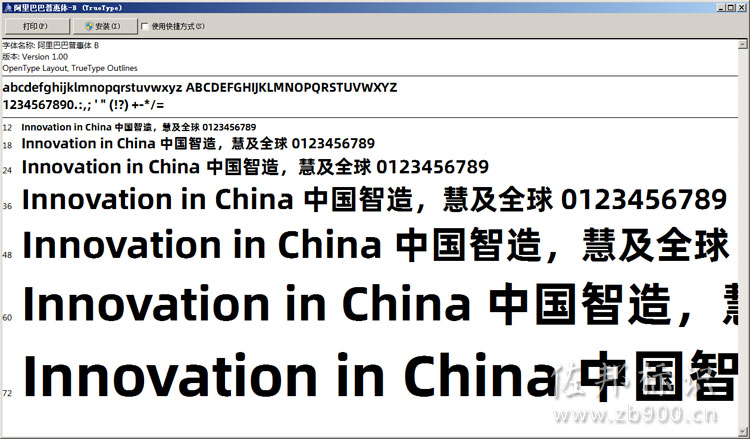
阿里巴巴普惠体优势
造以此字
献礼阿里巴巴20周年,细入微见字之美,用其字品商之道,阿里巴巴普惠体,让商业美而简单
多场景
中文5个字重,西文11个字重,满足多业务应用场景的组合表现需求。
全球化
收录11.6万汉字,7205个拉丁字母,覆盖173个语种,满足阿里巴巴集团及其生态的全球化业务需求。
年轻化
笔画简洁,造型瘦长,重心较高,充分展现20岁阿里少年额精气神。
这一次可免费商用的阿里巴巴普惠体共有 Light / Regular / Medium / Bold / Heavy 5个字重,其中 L/R/M/B 4个字重按照 GB18030 字符集标准制作,各包含 28983 个字符,而 H 则遵循 GB2312 标准,包含 8213 个字符,西文部分汉仪字库西文组扩展了日文假名、汉语拼音、台湾注音符号等,最终共计 124145 个字符。可以满足阿里巴巴集团及其经济体公司在全球化业务下的多个应用场景需求。
据阿里巴巴定制字体项目负责人、阿里巴巴集团品牌-高级创意设计专家羿光介绍,从去年 6 月至今,整套阿里巴巴普惠体的设计历时 10 个月,“不仅要包含突显企业品牌个性的标题字,还要囊括更为实用的内文字,兼顾多个场景下的应用……这么大体量的字体设计并面向全场景开放授权免费商用,开创了中国企业造字的先河。”
中文字体多采用现代简洁的笔画,造型上偏瘦长,并将字的重心提高,以展现 20 岁阿里巴巴少年的精气神。字体笔画上也做了一些简化,如标题字省略出脚部分,更显简洁。
不同于以往的家族字统一化处理,阿里巴巴普惠体针对不同字重的使用场景,对细节做了区别化处理。其中 L/R/M 较细的字体更适用于长文阅读,贴近底部的“口”字保留了出脚,更好的平衡了阅读时的流畅感,而 B/H 两款较粗的字体更适用于标题场景,为了保证简洁的质感,切除了出脚,从而更容易体现出块面感。
家族字体的不同粗细我们称之为”字重“,不同字重的字体承担着不同的作用,同时也有不同的使用规则。越细的字体反而不适用于字号非常小的字,具体的使用效果要在实际应用中去测试,从而选择出字重合适的字体。
这一次可免费商用的阿里巴巴普惠体共收录 116,895 个全形汉字(含 5 个字重),西文 Alibaba Sans 共 7,205 个拉丁字母(2 种风格、共 11 个字重),覆盖 172 个语种(覆盖大部分欧语国家),并可以满足阿里巴巴集团及其经济体公司在全球化业务下的多个应用场景需求。